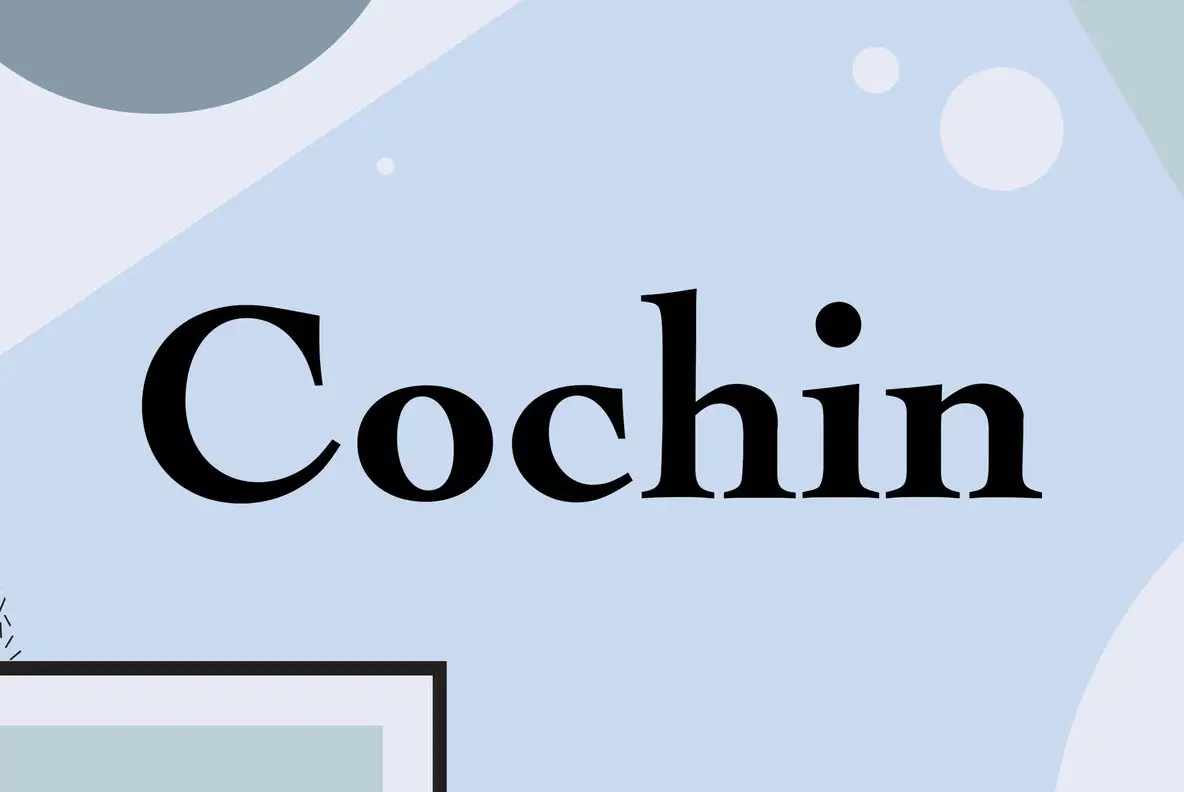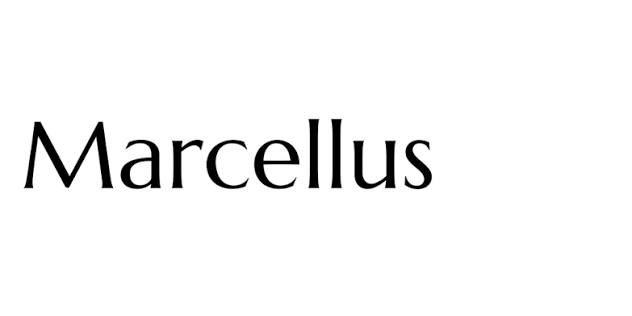
Font Spa Việt hóa là bộ sưu tập các phông chữ mang phong cách thanh lịch, tối giản, nhẹ nhàng và mang lại cảm giác thư thái, an tĩnh cho người xem. Được tuyển chọn kỹ lưỡng từ các dòng Serif thanh nhã, Script bay bổng hoặc Sans-serif trung tính, nhóm phông chữ này là lựa chọn hoàn hảo cho các thiết kế bộ nhận diện thương hiệu spa, thẩm mỹ viện, trung tâm chăm sóc sức khỏe và bao bì mỹ phẩm thiên nhiên. Doozypack.vn cung cấp link tải trọn bộ Font Spa Việt hóa Free chuẩn kỹ thuật, giúp bạn sở hữu kho phông chữ đẳng cấp, hỗ trợ đầy đủ tiếng Việt để tự tin thiết kế bao bì và bộ nhận diện thương hiệu chuyên nghiệp.
Đặc điểm thẩm mỹ của các dòng font Spa Việt hóa
Ngành dịch vụ làm đẹp và chăm sóc sức khỏe đòi hỏi ngôn ngữ thiết kế phải truyền tải được sự tin cậy, tính tịnh dưỡng và cảm giác thư giãn tuyệt đối cho khách hàng.
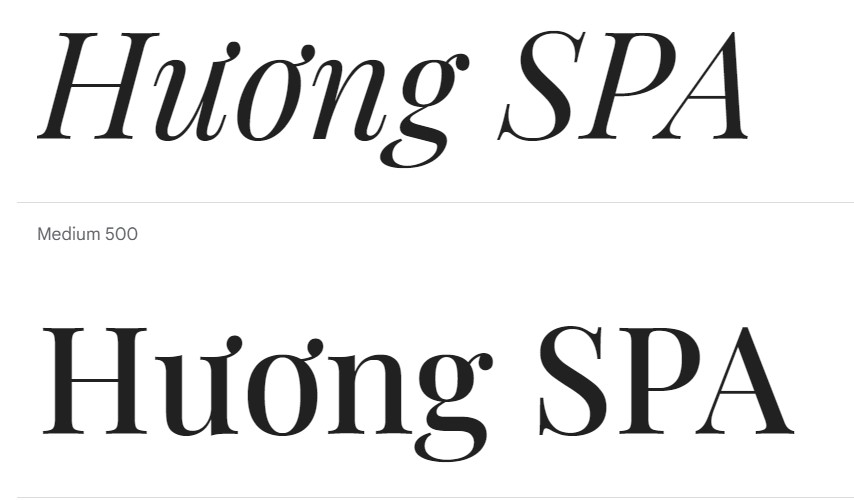
Phong cách tối giản (Minimalism) mang lại cảm giác an tĩnh
Đặc trưng lớn nhất của các bộ Font Spa Việt hóa là sự tiết chế tối đa các chi tiết rườm rà. Các ký tự sở hữu cấu trúc mở, khoảng trắng (space) rộng rãi và trục thẳng đứng trang nghiêm. Khi đặt các phông chữ này làm tiêu đề trên bao bì, thương hiệu của bạn sẽ ngay lập tức toát lên vẻ ngoài sạch sẽ, tinh khiết, minh bạch và vô cùng chuyên nghiệp.
Độ thông thoáng cao và các đường cong mềm mại
Bên cạnh các dòng phông chữ hình học, các bộ font dùng cho spa thường kết hợp thêm các đường nét uốn lượn nhẹ nhàng (như dòng Serif chuyển tiếp hoặc Script thanh mảnh). Sự kết hợp này mô phỏng hình ảnh của thiên nhiên, làn sóng nước hay cánh hoa, đánh thức cảm giác thư thái và chăm sóc tận tâm ngay từ cái nhìn đầu tiên trên vỏ hộp sản phẩm.
Ưu điểm nổi bật của bản Font Spa Việt hóa Free
Khi ứng dụng các phông chữ thư giãn vào thị trường trong nước, sự chỉn chu về dấu câu là yếu tố quyết định đến tính chuyên nghiệp của ấn phẩm:
- Khắc phục triệt để lỗi dấu tiếng Việt: Phiên bản Việt hóa đã được đội ngũ thiết kế trau chuốt thủ công từng dấu câu. Các dấu sắc, huyền, hỏi, ngã, nặng được vẽ thanh mảnh, đặt ở vị trí thoáng đãng so với thân chữ, không gây cảm giác chắp vá hay đè nét làm mất tính thẩm mỹ.
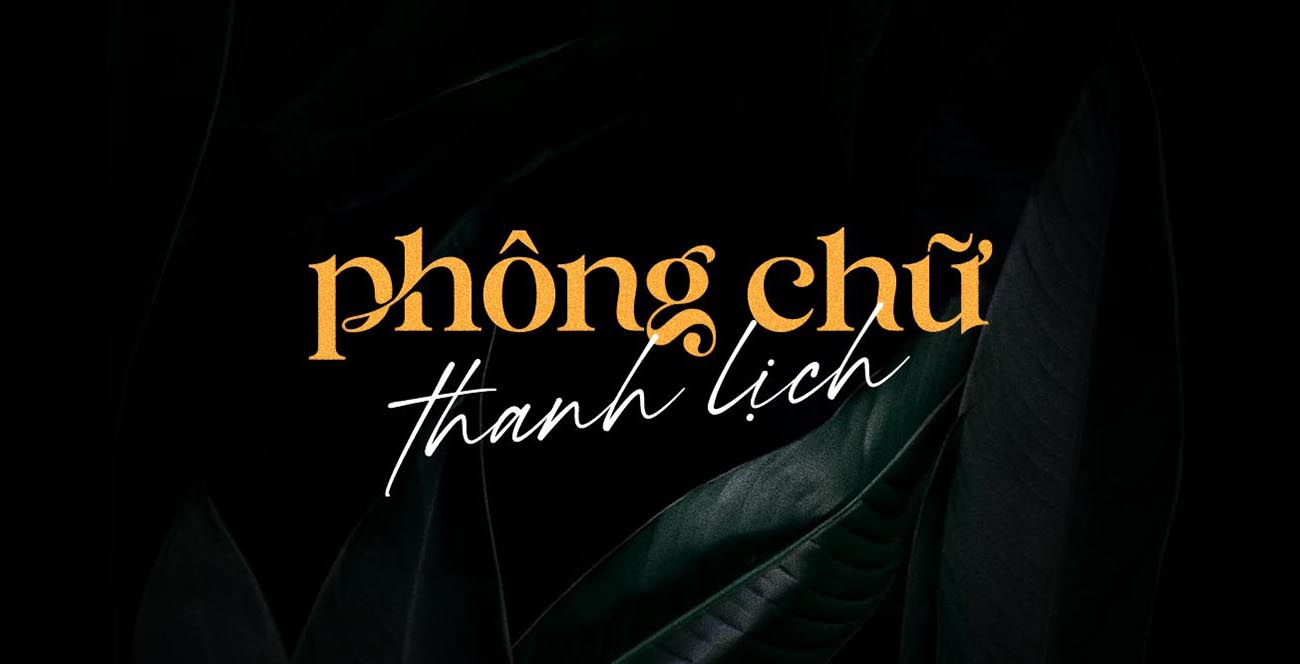
| Nhóm Font Spa | Đặc điểm thị giác | Ứng dụng đề xuất tại Doozypack.vn |
| Serif Tối Giản (Elegant Serif) | Thanh lịch, sắc sảo, quý phái | Làm logo Spa, tiêu đề hộp quà tặng mỹ phẩm cao cấp. |
| Sans-serif Trung Tính (Clean Sans) | Sạch sẽ, minh bạch, hiện đại | Dùng cho bảng thành phần, hướng dẫn sử dụng, tem nhãn. |
| Script Thư Thái (Soft Script) | Mềm mại, bay bổng, thư giãn | Thiết kế voucher, thư cảm ơn, nhãn chai tinh dầu. |
Ứng dụng thực tế của font Spa trong sản xuất bao bì tại Doozypack.vn
Sự tinh tế và thư thái của nhóm font này mang lại hiệu ứng thị giác đắt giá trên các dòng sản phẩm bao bì thực tế do Doozypack.vn sản xuất:
- Hộp giấy đựng Tinh dầu & Nến thơm: Tiêu đề thương hiệu in bằng font Serif thanh lịch kết hợp kỹ thuật ép kim mờ (Matte Gold) trên nền hộp màu Pastel tạo nên vẻ đẹp sang trọng và thư giãn.
- Bao bì Mỹ phẩm thiên nhiên & Skincare: Nét chữ tối giản kết hợp hoàn hảo cùng chất liệu giấy Ivory cán màng mờ, giúp vỏ hộp toát lên vẻ thuần khiết, an toàn và chuyên nghiệp.
- Túi giấy boutique thời trang & Spa: Tên cửa hàng in bằng phông chữ Spa màu đen tối giản trên nền túi giấy trắng giúp khẳng định gu thẩm mỹ tinh tế và dịch vụ chăm sóc tận tâm.
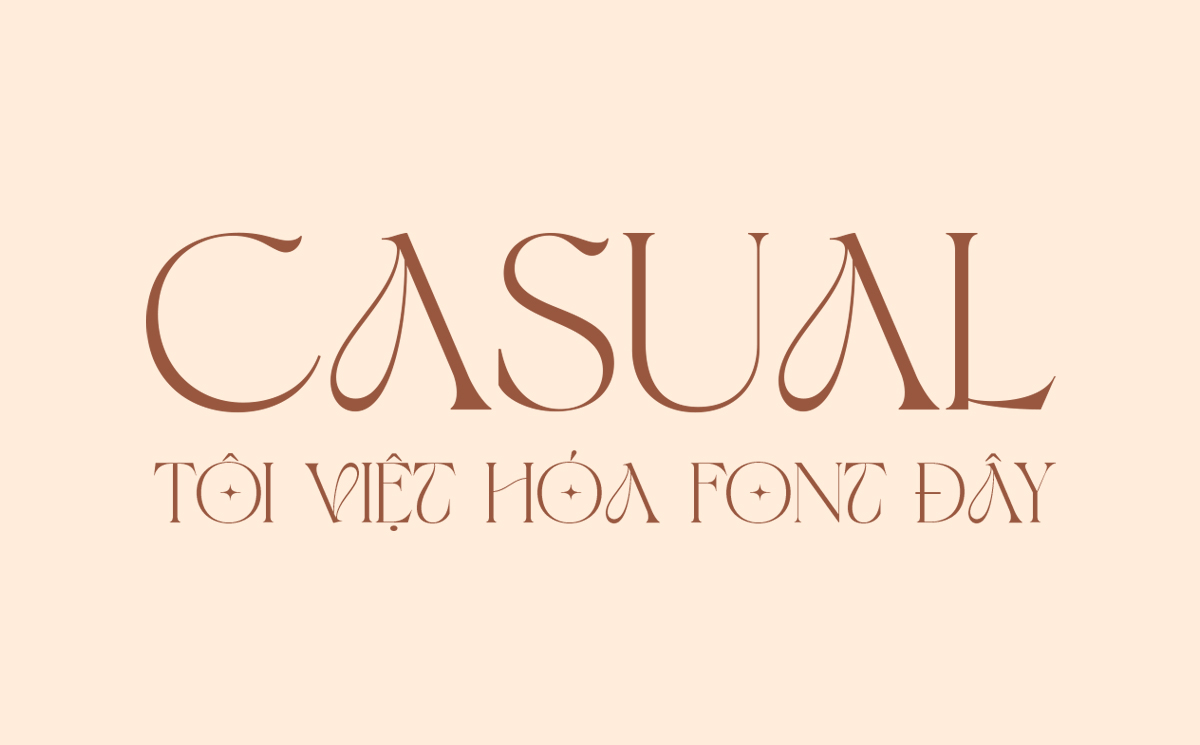
03 Lưu ý kỹ thuật khi in ấn với phông chữ thanh mảnh phong cách Spa
Việc sản xuất bao bì thực tế sử dụng các phông chữ thanh mảnh đòi hỏi sự am hiểu kỹ thuật chuyên sâu tại xưởng in Doozypack.vn:
- Kiểm soát độ dày nét Hairline khi gia công: Các nét ngang và chân chữ của font Spa khá mảnh. Khi gia công ép kim vàng (Hot Stamping) hoặc dập nổi, designer nên đảm bảo nét chữ có độ dày tối thiểu 0.15mm để nhũ bám dính sắc nét, không bị đứt đoạn.
- Chọn chất liệu giấy phẳng mịn: Font Spa đẹp nhất khi in trên giấy Ivory, Couche hoặc giấy mỹ thuật nhẵn. Tránh in các nét chữ quá thanh trên bề mặt giấy Kraft thô nhám vì mực dễ bị loang làm mất đi độ sắc sảo của nét chữ.
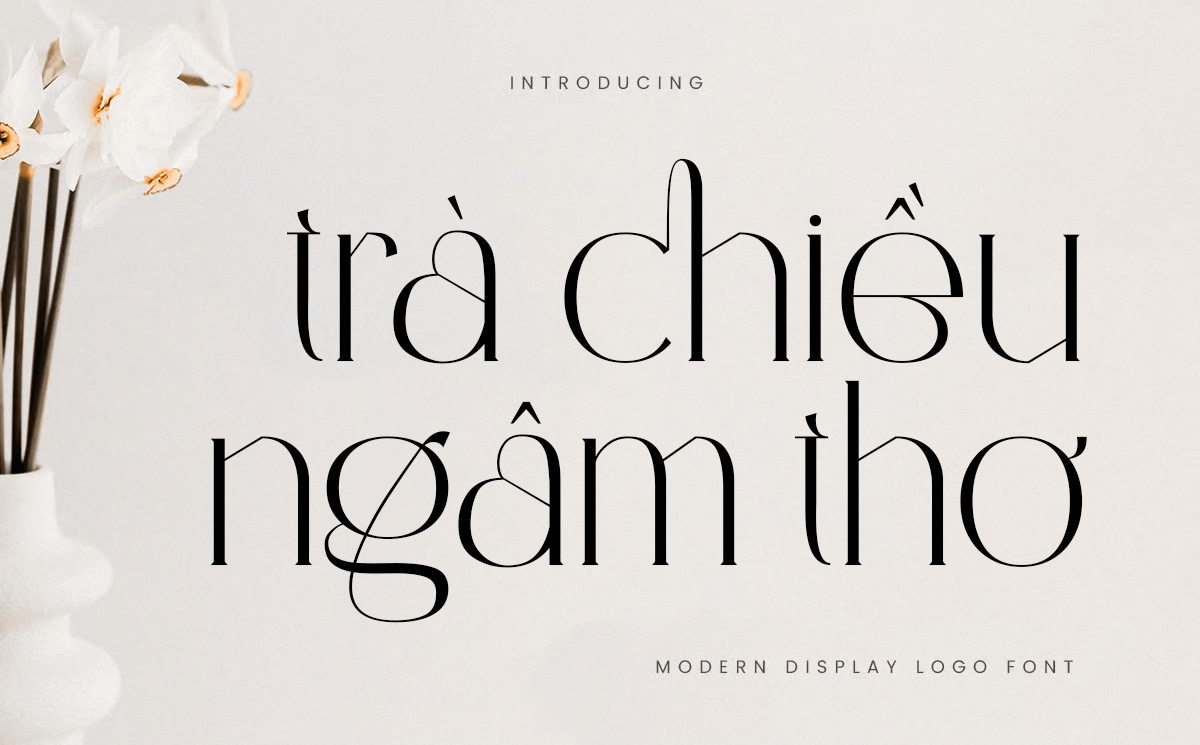
Doozypack.vn không chỉ cung cấp kho tài nguyên thiết kế miễn phí chất lượng cao mà còn trực tiếp sản xuất hộp giấy, túi giấy và tem nhãn theo yêu cầu. Với nét chữ thanh lịch, mềm mại và giàu tính thẩm mỹ, Font Spa phù hợp để tạo điểm nhấn cho tên thương hiệu, thông điệp hoặc các chi tiết nhận diện trên bao bì. Đội ngũ kỹ thuật viên sẽ hỗ trợ kiểm tra file, cân chỉnh bố cục và kích thước để từng đường nét khi in lên giấy được thể hiện rõ ràng, sắc nét và hài hòa. Font Spa đặc biệt phù hợp khi ứng dụng trên các mẫu túi giấy in logo, giúp tổng thể bao bì trở nên tinh tế và dễ ghi nhớ.